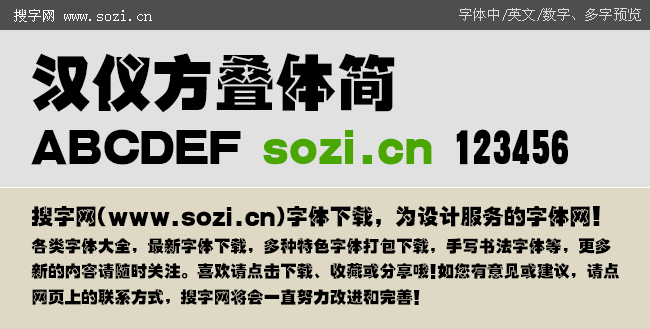
漢儀方疊體簡(jiǎn)
漢儀方疊體簡(jiǎn)體是搜字網(wǎng)給大家提供一款漢儀字體公司出品中文字體下載,漢儀方疊體有簡(jiǎn)繁兩個(gè)版本,此為簡(jiǎn)體版,這是一款很具藝術(shù)效果和設(shè)計(jì)感字體,打出來的字就像是用紙片疊起來的效果,非常好看,海報(bào)標(biāo)題等適用,相信你一定會(huì)喜歡在自己作品中用到這款中文字體!